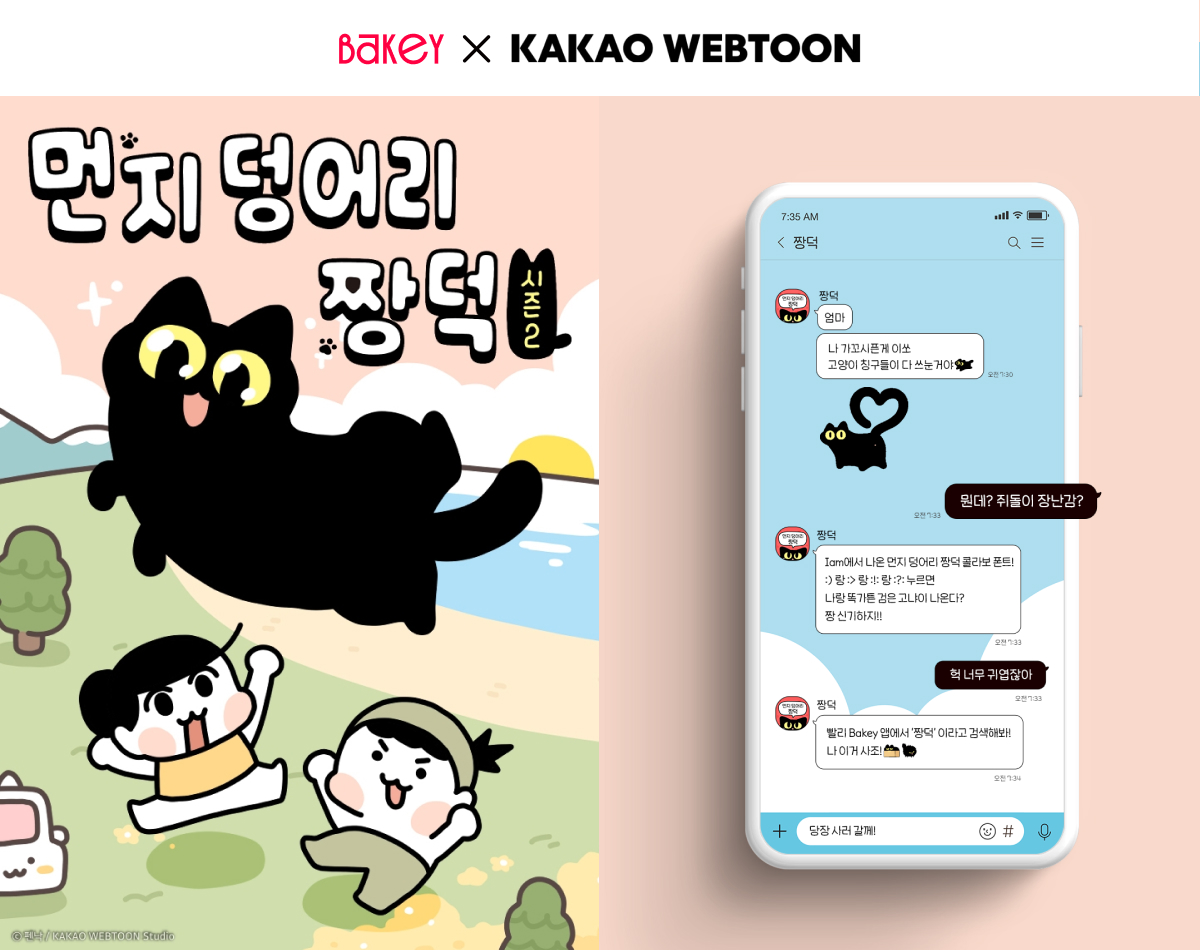
- 인기 캐릭터툰 ‘먼지 덩어리 짱덕’과 협업, 모바일 폰트 ‘Iam 먼지덩어리짱덕’ 출시
- 폰트 IP의 활용 범위를 엔터테인먼트·콘텐츠 영역 전반으로 확장하며, 폰트의 산업적 확장성 강화
콘텐츠 크리에이터 플랫폼 기업 산돌(대표이사 윤영호)의 모바일 폰트 서비스 베이키(Bakey)가 카카오엔터테인먼트의 웹툰 플랫폼 카카오웹툰과 함께 인기 캐릭터툰 ‘먼지 덩어리 짱덕’과 협업한 모바일 폰트 ‘Iam 먼지덩어리짱덕’을 출시하고, 이를 기념한 무료 이용권 및 할인 이벤트를 진행한다.
이번 협업은 1020세대 팬덤이 강한 웹툰 IP와 모바일 폰트의 결합으로 폰트 활용 영역을 즐기는 엔터테인먼트로까지 확장하여 경험하도록 제공하기위해 기획됐다. 양사는 인기 캐릭터 IP의 감성을 모바일 텍스트 입력 환경에서 경험하도록 하여 단순한 글자 입력이 즐거움이 되는 경험을 제공하고 싶다는 바램에 공감했다.
‘Iam 먼지덩어리짱덕’은 카카오웹툰의 인기 캐릭터툰 ‘먼지 덩어리 짱덕’ 속 캐릭터 ‘짱덕’을 활용해 개발된 모바일 전용 폰트로 모바일 폰트 플랫폼 '베이키'에서 구매 가능하다.
작품을 집필한 펜낙 작가의 손글씨 스타일과 웹툰 특유의 몽글몽글하고 귀여운 아이덴티티를 폰트 디자인에 그대로 담아낸 것이 특징이다. 특히 타이핑 과정에서 특정 문자를 조합하면 캐릭터 일러스트가 등장하는 ‘히든 딩뱃(Hidden Dingbat)’ 기능을 적용해, 입력 자체가 하나의 놀이 경험이 되도록 설계했다. 해당 딩뱃에는 컬러 폰트 기술이 적용돼, 지원 환경에서는 짱덕 캐릭터와 어울리는 통통 튀는 색감을 그대로 구현할 수 있다.